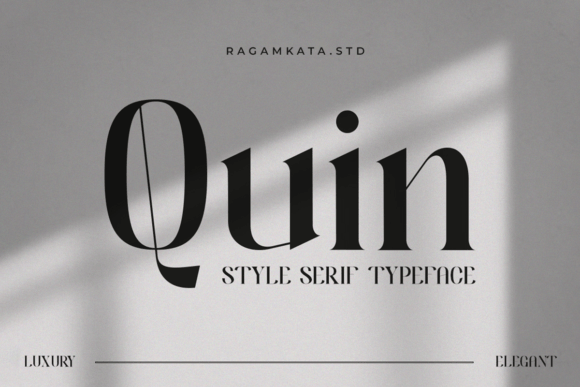
Quin
Quin와 같은 κ³ ν’ˆμ§ˆ μžμ‚°μ„ μ°Ύκ³  μžˆλ‹€λ©΄ 이 프리미엄 νŒ¨ν‚€μ§€λŠ” 창의적인 ν”„λ‘œμ νŠΈλ₯Ό μœ„ν•œ ν™˜μƒμ μΈ μ„ νƒμž…λ‹ˆλ‹€.
μ •λ°€ν•˜κ²Œ μ œμž‘λœ QuinλŠ” κΉ”λ”ν•œ 벑터, λΆ€λ“œλŸ¬μš΄ νƒ€μ΄ν¬κ·Έλž˜ν”Ό 및 μ•ˆμ‹¬ν•  수 μžˆλŠ” μƒμ—…μš© λΌμ΄μ„ μŠ€λ₯Ό μ œκ³΅ν•©λ‹ˆλ‹€.
POD(μ£Όλ¬Έν˜• 인쇄) μ œν’ˆ, κ²°ν˜Όμ‹ μ΄ˆλŒ€μž₯ λ˜λŠ” μ†Œμ…œ λ―Έλ””μ–΄ κ·Έλž˜ν”½μ„ λ§Œλ“€ λ•Œ QuinλŠ” 이상적인 μ„ νƒμž…λ‹ˆλ‹€.